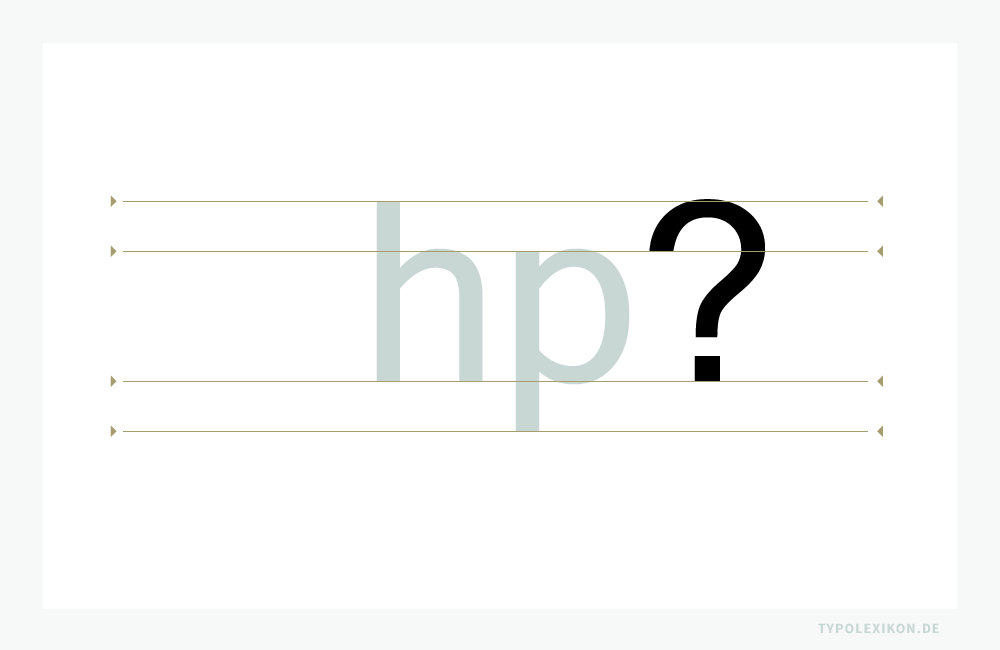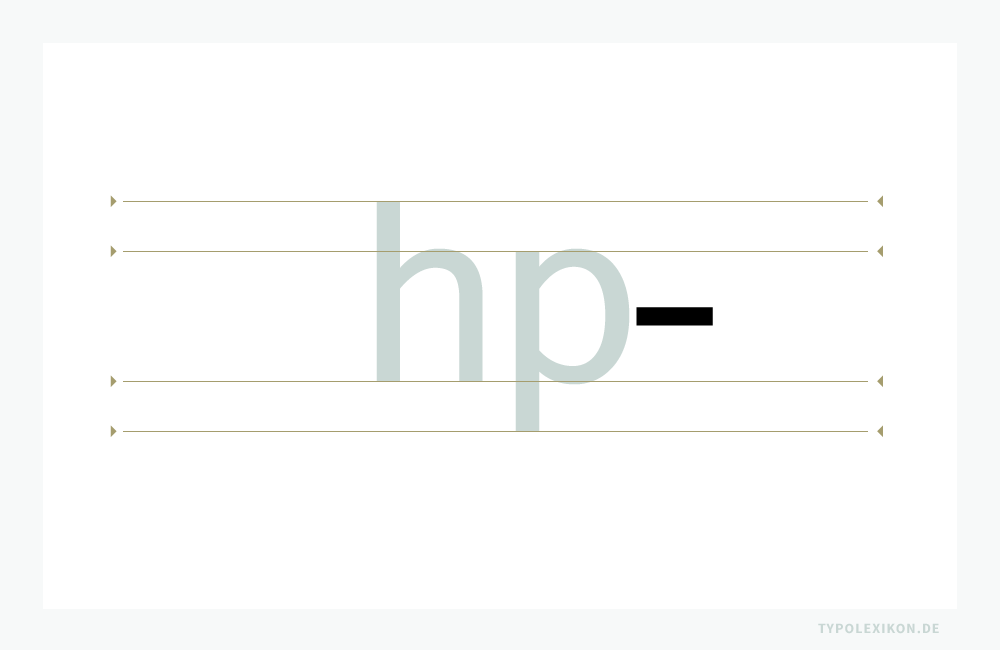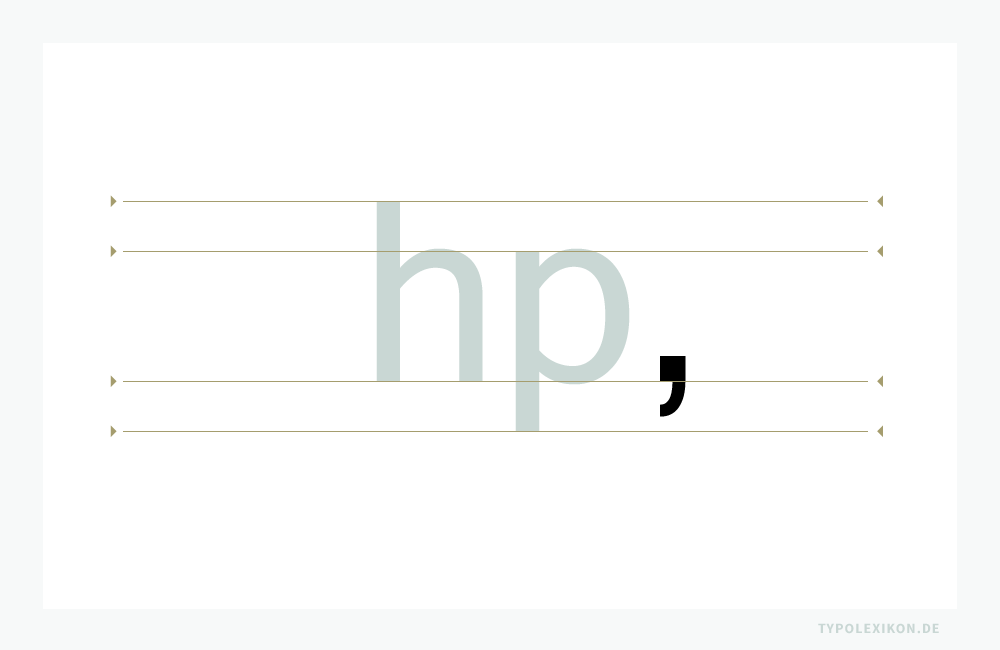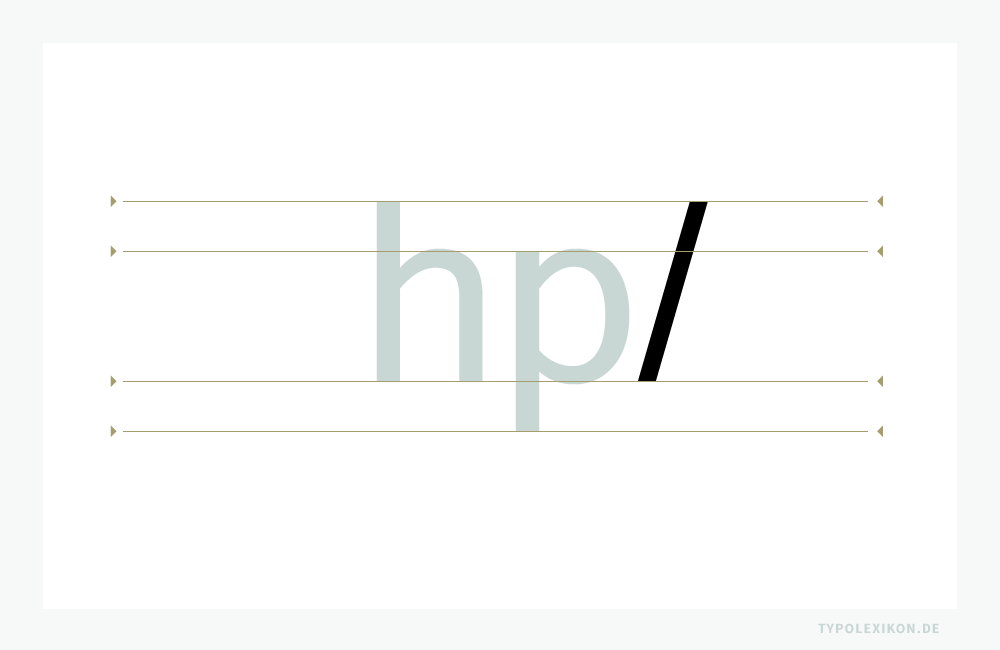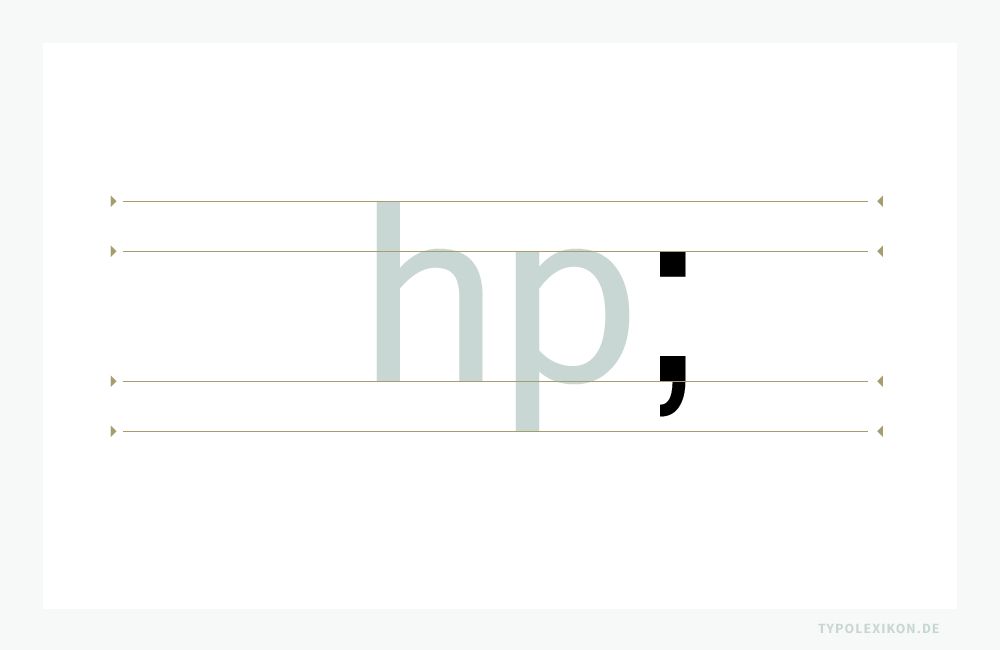
Interpunktionszeichen
Interpunktionszeichen sind orthographische Satzzeichen, um eine geschriebene Wortsprache verständlich zu formulieren, Worte in Bezug zueinander zu setzen, auseinanderzuhalten und deren Reihung zu Satzgebilden zu ermöglichen. Interpunktionszeichen dienen der Sprachfixierung (grammatische Funktion).
In der Typografie zählen Interpunktionszeichen zu den Sonderzeichen. Die korrekte Verwendung von orthographischen Satzzeichen im deutschen Schriftsatz wird vom »Rat für deutsche Rechtschreibung« vorgegeben. 1)
Des Weiteren wird die Nutzung von Interpunktionszeichen vom Deutschen Institut für Normung e.V. (DIN) 2) in der DIN 5008 »Schreib- und Gestaltungsregeln für die Textverarbeitung« beschrieben.
Im deutschsprachigen Schriftsatz zählen zu den Interpunktionszeichen bzw. orthographische Satzzeichen:
Anführungszeichen
Optische Auszeichnung von wörtlich wiedergegebenen Äußerungen (direkter Rede) und Textstellen (Zitate) sowie zur Hervorhebung von Wortteilen, Wörtern oder Satzteilen. Details siehe Anführungszeichen und Französische Anführungszeichen.
Das »Anführungzeichen« ist ein Interpunktionszeichen. Der Stand des orthographischen Satzzeichens ist anhand der vier Hauptschriftlinien und der hp-Vertikalhöhe skizziert, wobei es von Schrift zu Abweichungen kommt. Beispiel gesetzt in der »Microsoft Sans Serif«, einer Systemschrift von Microsoft®.
Der Stand dieses und der nachfolgenden orthographischen Satzzeichen ist anhand der vier Hauptschriftlinien und der hp-Vertikalhöhe skizziert. Beispiele gesetzt in der »Microsoft Sans Serif«, einer Systemschrift von Microsoft®.
Apostroph, Ausfallzeichen oder Auslassungszeichen
Der Apostroph dient als Auslassungszeichen für einen oder mehrere Buchstaben, zur Markierung des Genitivs von Eigennamen, die auf s, ss, ß, tz, z, x und ce enden, und kein Artikelwort bzw. kein Possessivpronomen bei sich haben sowie bei Ableitungen von Namen, die mit -sch gebildet werden. Details siehe Apostroph.
Der »Apostroph« ist ein Interpunktionszeichen. Der Stand des orthographischen Satzzeichens ist anhand der vier Hauptschriftlinien und der hp-Vertikalhöhe skizziert, wobei es von Schrift zu Abweichungen kommt. Beispiel gesetzt in der »Microsoft Sans Serif«, einer Systemschrift von Microsoft®.
Auslassungspunkte
Drei Punkte (Dreipunkt) – mit und ohne Klammern – stehen u.a. für eine Textauslassung oder eine Gesprächspause. Details siehe Auslassungspunkte.
Die »Auslassungspunkte« sind ein Interpunktionszeichen. Der Stand des orthographischen Satzzeichens ist anhand der vier Hauptschriftlinien und der hp-Vertikalhöhe skizziert, wobei es von Schrift zu Abweichungen kommt. Beispiel gesetzt in der »Microsoft Sans Serif«, einer Systemschrift von Microsoft®.
Ausrufezeichen oder Rufzeichen
Das Ausrufezeichen markiert das Ende eines Ausrufesatzes, einer Aufforderung oder eines Befehls. Das Ausrufezeichen gehört zu den Satzschlusszeichen.
Das »Ausrufezeichen« ist ein Interpunktionszeichen. Der Stand des orthographischen Satzzeichens ist anhand der vier Hauptschriftlinien und der hp-Vertikalhöhe skizziert, wobei es von Schrift zu Abweichungen kommt. Beispiel gesetzt in der »Microsoft Sans Serif«, einer Systemschrift von Microsoft®.
Divis, Bindestrich oder Trennstrich
Das Divis verknüpft zusammengehörende Teilbegriffe, Werte und Zahlen (siehe Zahlengliederung) und teilt Wörter am Zeilenende. Details siehe Divis.
Der »Bindestrich« ist ein Interpunktionszeichen. Er ist kürzer als der Gedankenstrich. Der Stand des orthographischen Satzzeichens ist anhand der vier Hauptschriftlinien und der hp-Vertikalhöhe skizziert, wobei es von Schrift zu Abweichungen kommt. Beispiel gesetzt in der »Microsoft Sans Serif«, einer Systemschrift von Microsoft®.
Fragezeichen
Das Fragezeichen steht am Ende einer Frage. Das Fragezeichen gehört zu den Satzschlusszeichen.
Das »Fragezeichen« ist ein Interpunktionszeichen. Der Stand des orthographischen Satzzeichens ist anhand der vier Hauptschriftlinien und der hp-Vertikalhöhe skizziert, wobei es von Schrift zu Abweichungen kommt. Beispiel gesetzt in der »Microsoft Sans Serif«, einer Systemschrift von Microsoft®.
Gedankenstrich oder Halbgeviertstrich
Der Gedankenstrich wird als Parenthesestrich, Gegenstrich, Auslassungsstrich, Bis-Strich, Spiegelstrich und als Minuszeichen verwendet. Details siehe Halbgeviertstrich.
Der »Gedankenstrich« ist ein Interpunktionszeichen. Er ist länger als der Bindestrich. Der Stand des orthographischen Satzzeichens ist anhand der vier Hauptschriftlinien und der hp-Vertikalhöhe skizziert, wobei es von Schrift zu Abweichungen kommt. Beispiel gesetzt in der »Microsoft Sans Serif«, einer Systemschrift von Microsoft®.
Kolon oder Doppelpunkt
Der Doppelpunkt beendet einen Satz und stellt gleichzeitig den Beginn einer wörtlichen Rede, einer Aufzählung, eines erklärenden Folgesatzes oder eines Zitats dar. Nach einem Kolon wird – je nach Satzaufbau – klein oder groß weitergeschrieben.